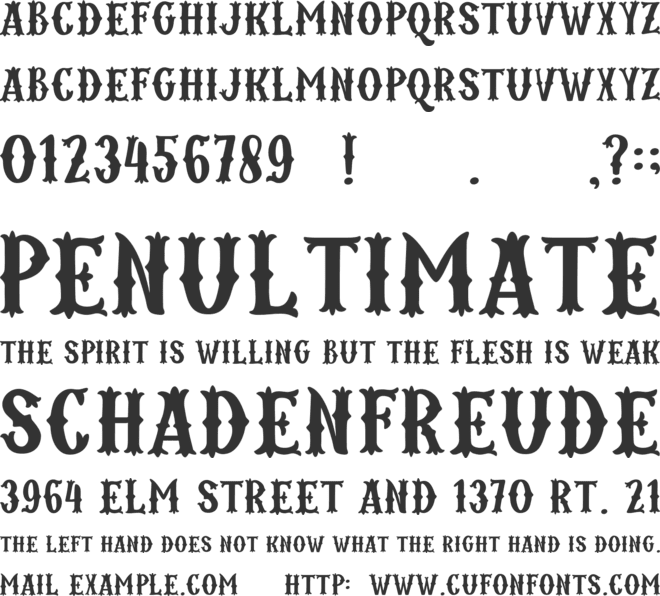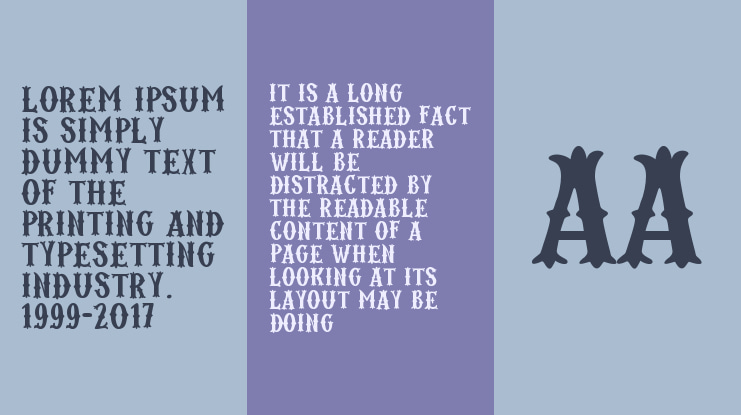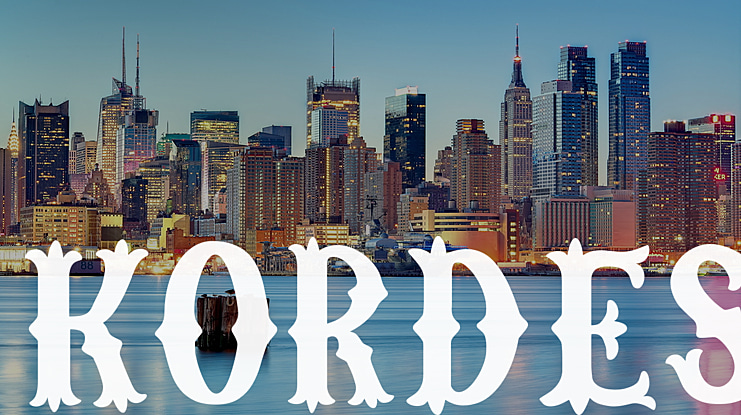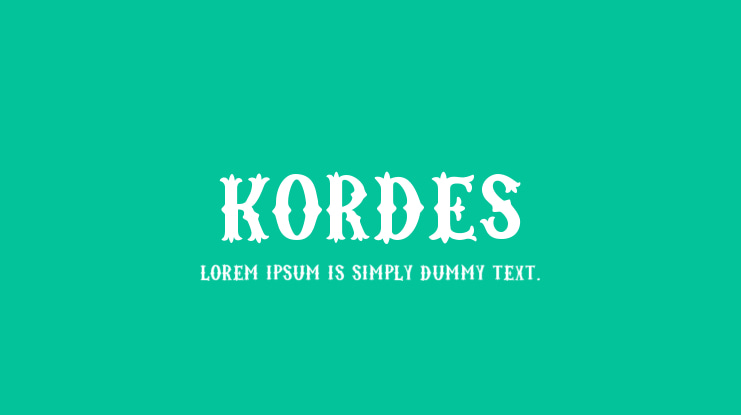
Kordes Font
Fontasi ini dipersembahkan untuk para kordes di luar sana, yang melanglang buana demi mencari jati diri melalui pelbagai media pelampiasan ekspresi, semisal knalpot brong, poni lempar atau gaya swafoto yang idiosinkratif. Fontasi ini, puji Tuhan, masih gratis untuk semuanya. Akui keberadaan mereka, sekarang!